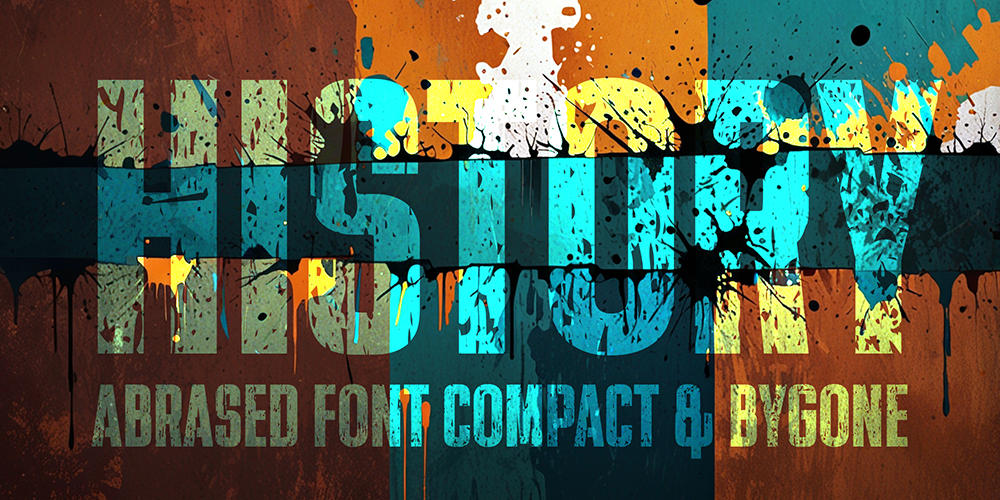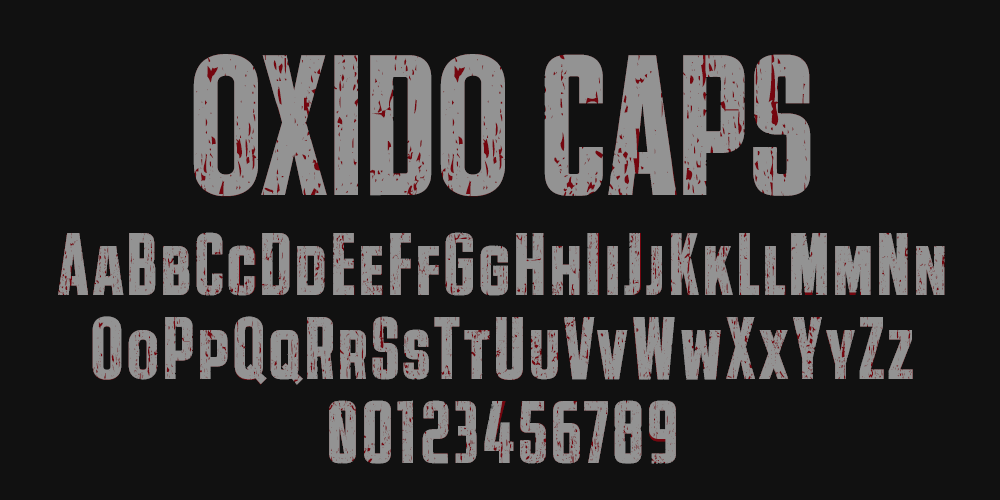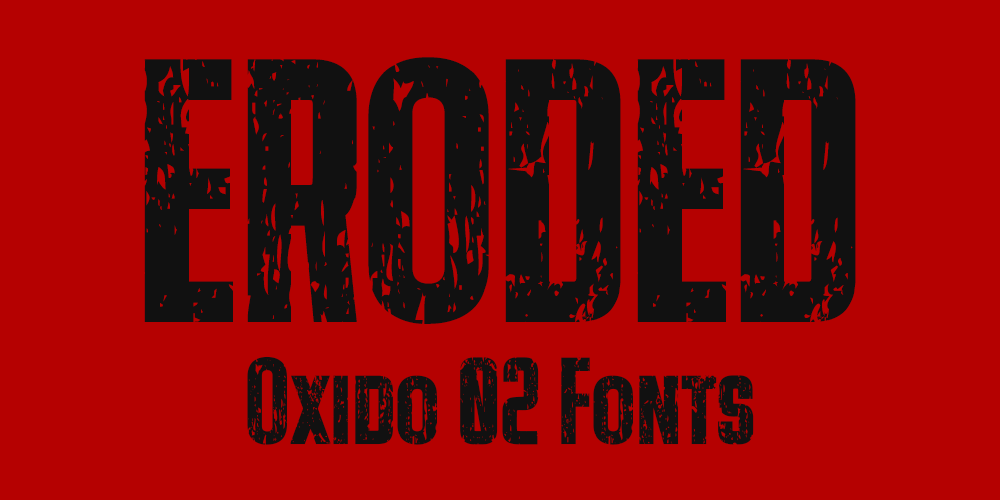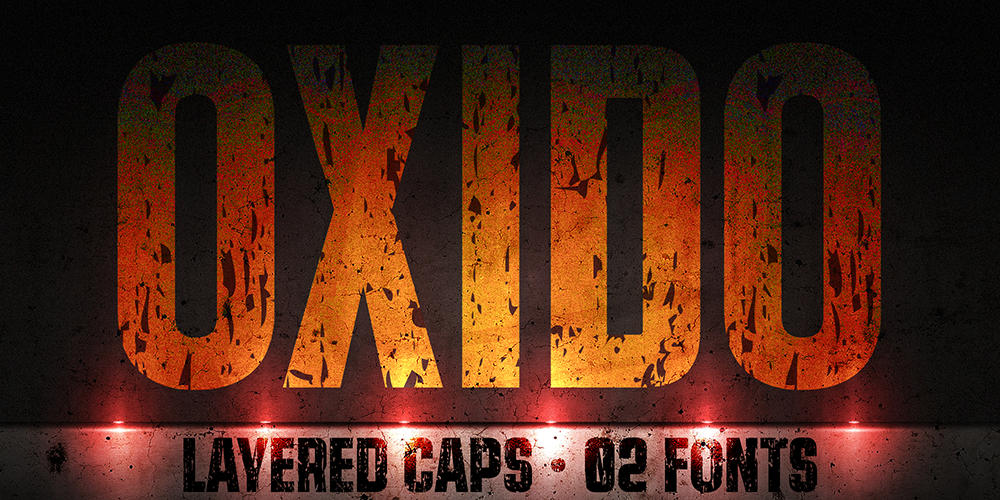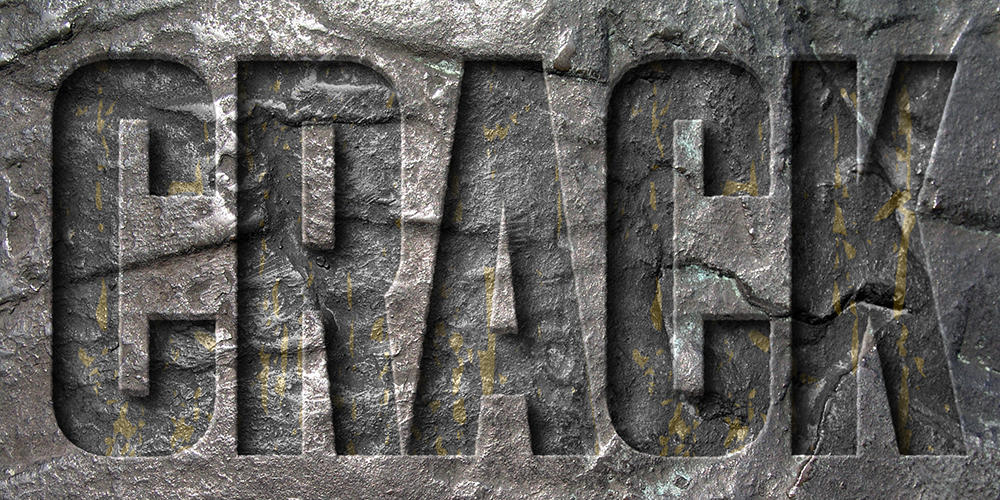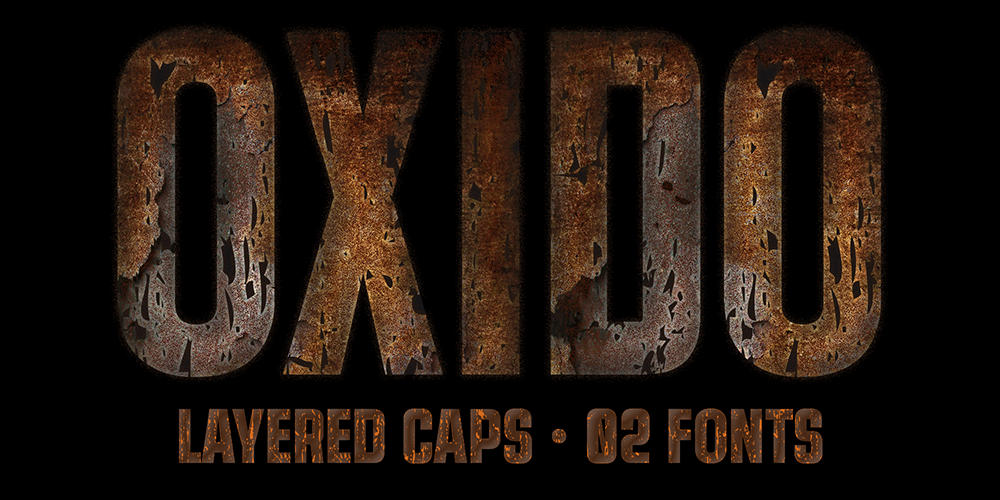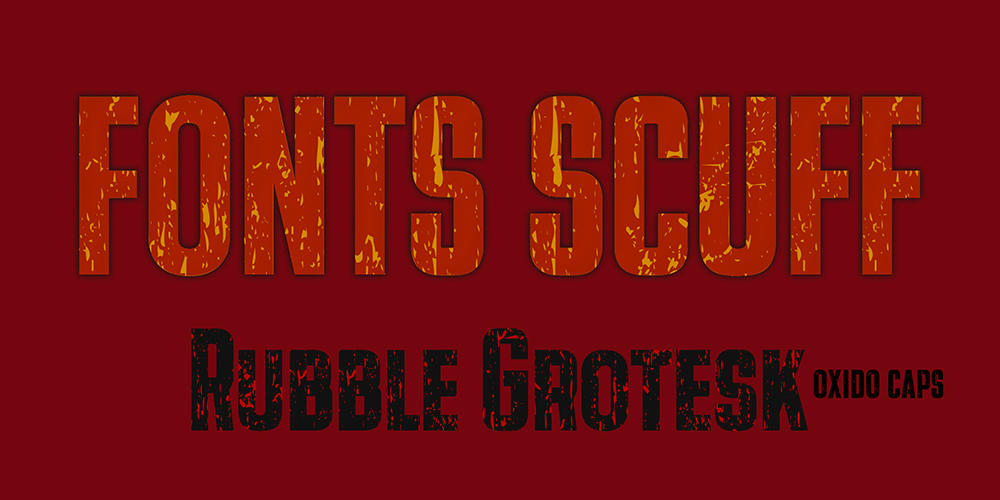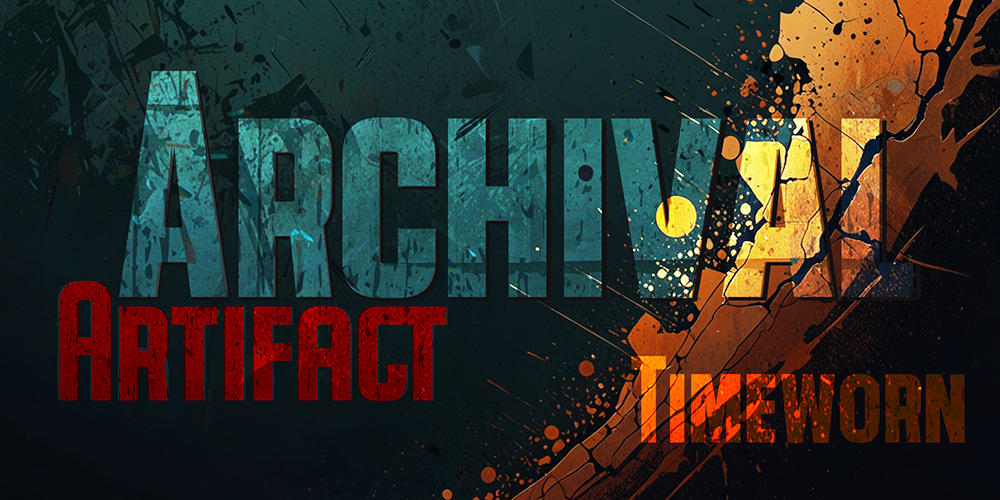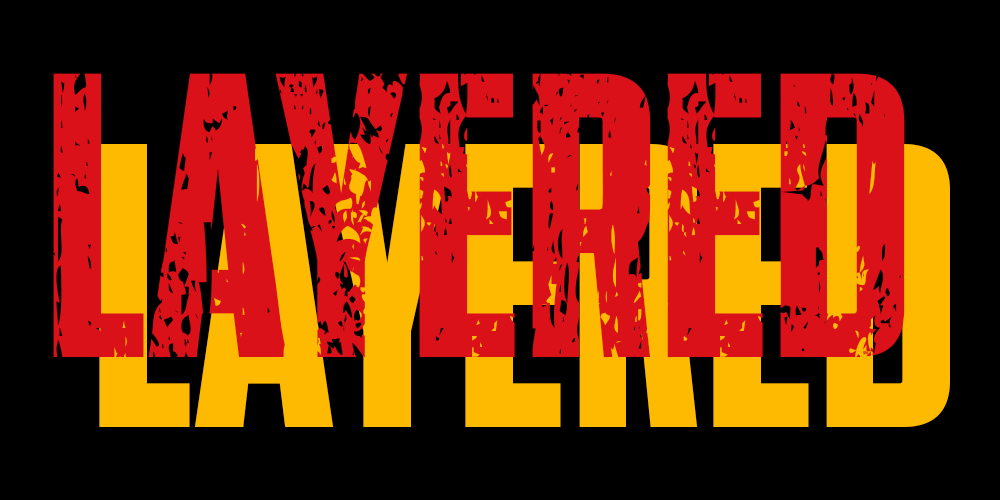
Layered fonts • Solid & Eroded
Estilo: Sans Serif, Capitals, Display, Layered. Eroded
Proporción: Ultra Condensed, Extra Bold
Oxido: la belleza de lo desgastado
Oxido nace de una idea poderosa: capturar la huella implacable del tiempo. La aspereza del óxido, la rudeza industrial y la belleza de lo imperfecto se funden en una tipografía que no sacrifica legibilidad ni sofisticación tipográfica.
No es solo una fuente erosionada —o “destrozada”—; es un testimonio visual de resistencia y autenticidad. Cada glifo de Óxido es una metáfora del paso del tiempo, combinando rigor técnico con fuerza expresiva.
Un carácter erosionado y auténtico
Oxido pertenece a la tradición de las tipografías erosionadas, desgastadas o destrozadas, un estilo que convierte las imperfecciones en narrativas visuales.
Cuando una letra se desintegra, revela su memoria: grietas que hablan de años de exposición, bordes irregulares que sugieren choques invisibles. Estas fuentes no buscan la perfección digital; buscan transmitir autenticidad, historia y emoción, evocando una estética industrial, urbana o incluso post-apocalíptica.
El reto de este estilo suele ser la legibilidad. Aquí es donde Oxido marca la diferencia: gracias a innumerables correcciones ópticas, cada glifo mantiene un equilibrio sorprendente. Su lectura es clara y directa, sin perder la intensidad visual de lo erosionado.
La versatilidad del estilo Layered
Oxido va más allá de la textura. Su sistema Layered abre un universo de posibilidades gráficas al permitir superponer capas y construir títulos en dos o más colores, generando un efecto de profundidad y dramatismo puramente tipográfico. Imagina una palabra donde la base sólida es de un rojo intenso y la capa superior erosionada en un dorado metálico. Te invito a superponerme, desgarrarme, colorearme:
Una tipografía con alma
Óxido no está hecha para suavizar, sino para recordarnos que la belleza también habita en lo erosionado, lo áspero y lo imperfecto. Es una tipografía con alma, capaz de contar historias desde lo visual y dejar huella en cada proyecto de diseño.
- Oxido Solid: La base maciza y contundente, extra condensada y limpia. Es el cimiento sobre el que se construye el efecto layered y una potente opción por sí sola para mensajes directos y contundentes. Perfecta para titulares directos, sólidos y sin concesiones.
- Oxido Eroded: El carácter texturizado, el desgaste refinado, la historia sobre la superficie. Esta versión aplica el efecto de desgaste de forma controlada, capturando la esencia de la oxidación, el paso del tiempo y elementos imperfectos sobre la superficie sólida.
Precisión técnica OTF
Detrás de su espíritu rebelde y áspero, Oxido es una tipografía construida con el mismo cuidado que un reloj de precisión. Parte de la estructura en mayúsculas de mi anterior tipografía Tighten Caps Bold, conservando su refinamiento métrico, un kerning ajustado con precisión y un sinfín de correcciones ópticas que garantizan fluidez y equilibrio en el texto.
Además, incorpora funciones avanzadas OpenType como números alternativos, fracciones dinámicas, versalitas y más, ofreciendo a los diseñadores un control profesional. Su soporte para Latin Extended-A asegura compatibilidad con una amplia gama de idiomas europeos.
Oxido está pensada para dominar superficies amplias y dejar una huella imborrable. Su potencia visual y flexibilidad la convierten en una opción ideal para:
- Diseño Editorial: en portadas editoriales que exigen urgencia y carácter, titulares de revistas o artículos.
- Cartelería y Posters: desde festivales de cine hasta conciertos, impactando a distancia y sorprendiendo de cerca.
- Branding & Identidad: para marcas que buscan transmitir autenticidad, robustez y un carácter atemporal.
- Packaging: cervezas artesanales, destilerías, productos rústicos o de carácter industrial que necesiten una presencia fuerte y texturizada.